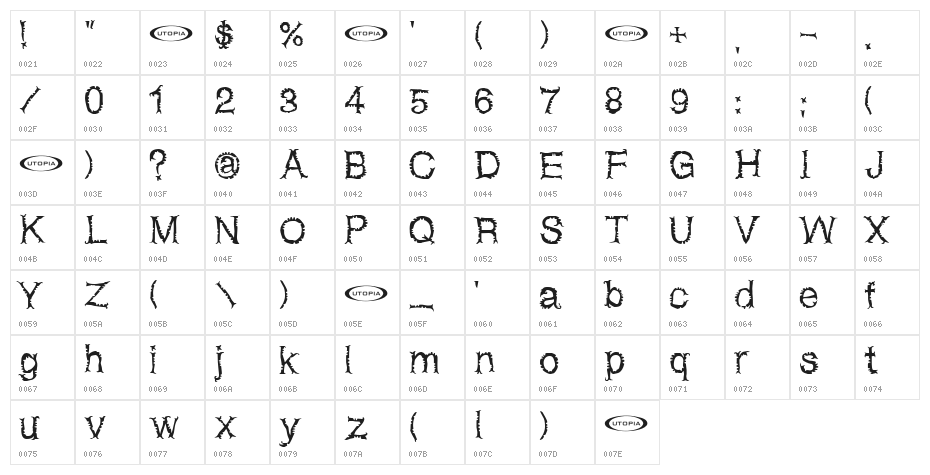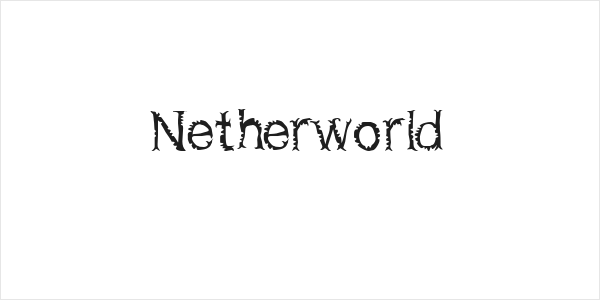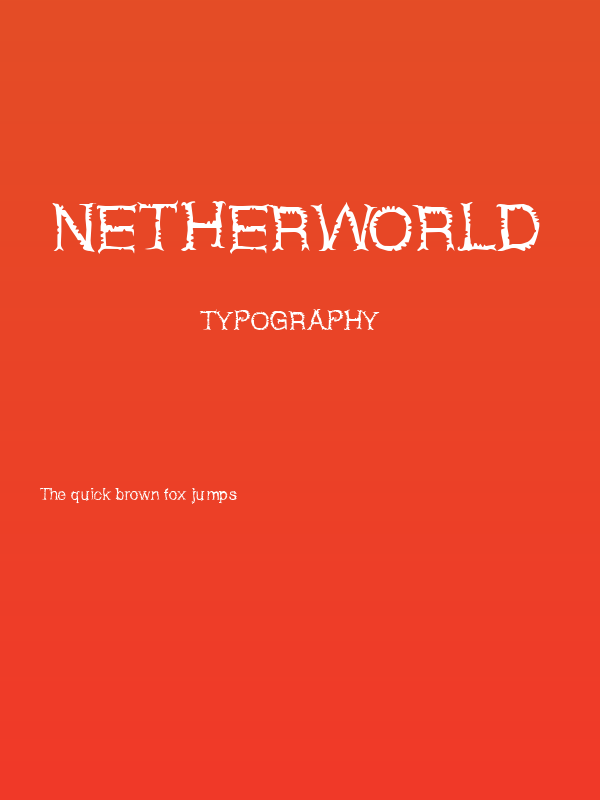
Netherworld Font
| Gesamtstil | Gothic, Dramatic |
| Vorgeschlagene Projekte | Horror-themed posters, Halloween invitations, fantasy book covers, video game titles. |